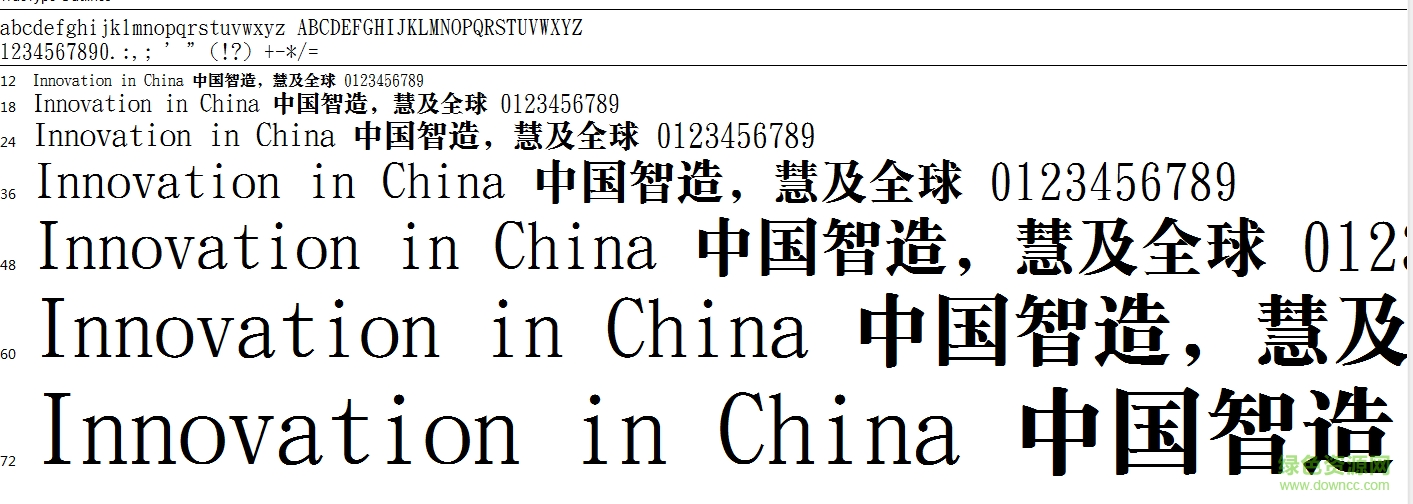
華康簡(jiǎn)標(biāo)題宋字體
dfsong-xb-80-win-gb字體又叫華康簡(jiǎn)標(biāo)題宋 win10版字體,該字體雅致清晰,氣質(zhì)出眾,當(dāng)出行win10無(wú)法安裝時(shí),大家可以嘗試將Windows Firewall服務(wù)啟用一下,然后重啟電腦按照以下方式安裝字體!
宋體由來(lái)
北宋的畢升發(fā)明了活字印刷,刻字在楷書體上產(chǎn)生了一種橫輕直重,閱讀醒目的印刷體,后稱宋體。到了明宋代演變?yōu)楣P劃?rùn)M細(xì)堅(jiān)粗,字形方正的明體。當(dāng)時(shí)民間流行一種橫劃很細(xì),而堅(jiān)劃特別粗壯,字形扁扁的洪武體,如職官的銜牌、燈籠、告示等都采用這種字體
dfsong-xb-80-win-gb字體
宋體特點(diǎn)
橫細(xì)堅(jiān)粗,“撇如刀,點(diǎn)如瓜子,捺如掃”筆劃嚴(yán)謹(jǐn),帶有裝飾性的點(diǎn)線,字形方正典雅,嚴(yán)肅大方,是美術(shù)字體之首。